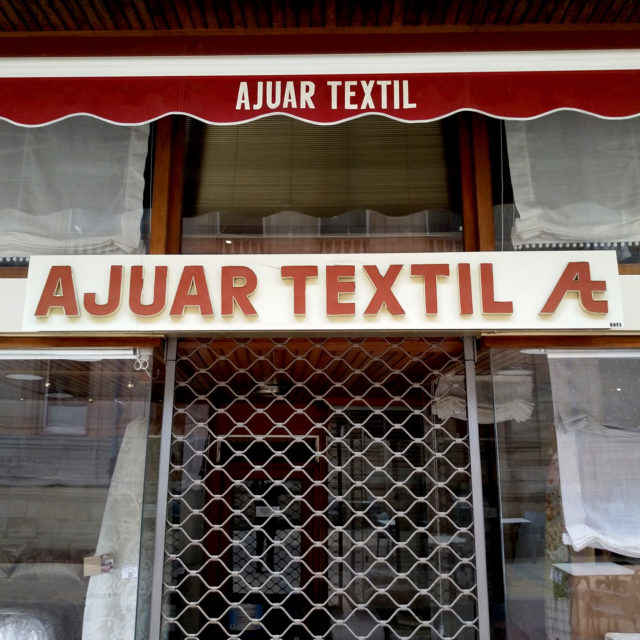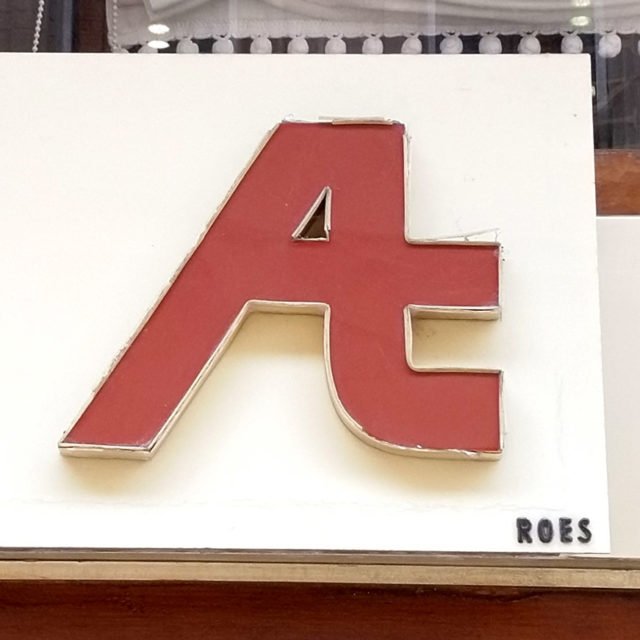
Ajuar Textil
Comercio de Torrelavega fundado en 1978 por Félix y que sigue abierto; desde entonces ha sido uno de los referentes de la ciudad en cortinas, estores, ropa de cama y tapicería.
La foto de archivo ha sido enviada por Sara Fernández para el proyecto, e ilustra la imagen que salió en El Diario Montañés el día de la inauguración de la tienda.
Destaca su rótulo, hecho por ROES (empresa de la que aún se pueden ver algunas muestras por otras localidades) donde hay un precioso monograma con la A y la T minúscula. Gracias a la redes sociales, hemos tenido la fortuna de conocer al autor de este diseño. Se llama Rafael Crespo, y esperamos poder hablar con el sobre el oficio y la historia de la empresa. Creemos que esto es importante ponerlo en valor, porque a veces solo vemos las tipografías y composiciones, pero no vemos a quienes están detrás en su diseño y creación.